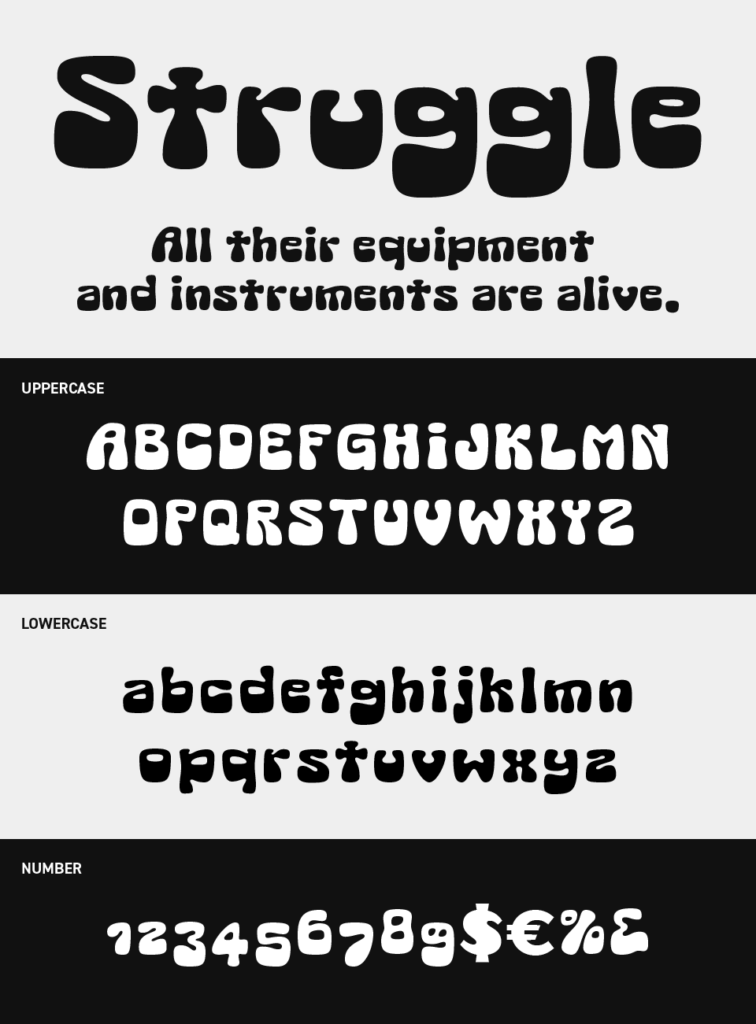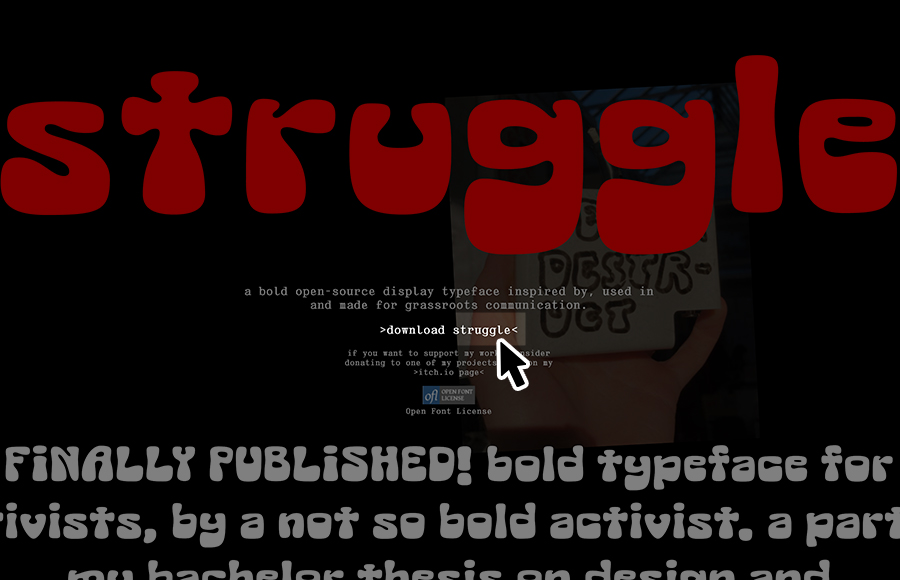
Struggleフォントは、ふっくらと膨らんだシルエットが印象的なポップ系ディスプレイフォントです。
手書きで書いた太めの線と、角のない丸みと均一な太さが、やわらかく愛嬌のある雰囲気を生み出し、一気に親しみやすい空気に変えてくれるフォントです。
文字同士が並んだときの弾むようなリズム感も心地よく、キッズ向けコンテンツやポップカルチャー系のビジュアル、カジュアルなロゴ制作にも相性が良いフォントです。